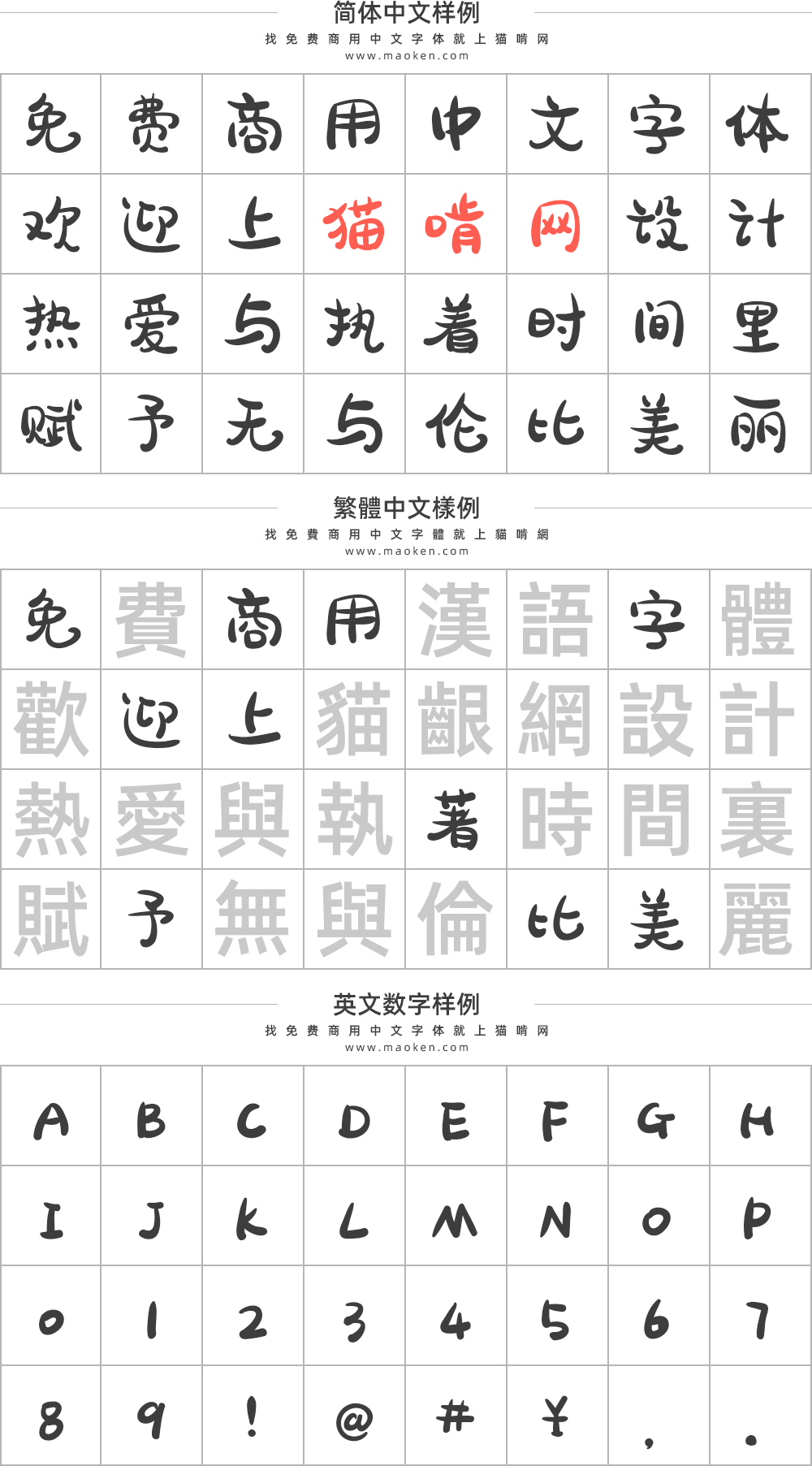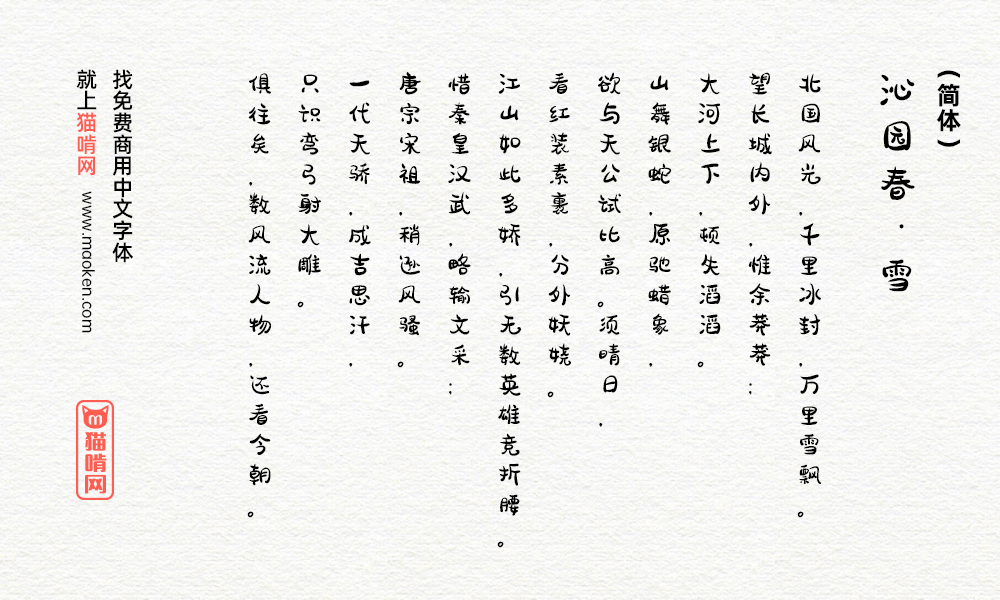
胡晓波骚包体:这个胡晓波是真的非常骚
字体作者:胡晓波 (中国大陆) 字体字重:1个
字体作者:胡晓波工作室(中国大陆)字体字重:1个
2019年12月23日,在圣诞节前夕,站酷人气设计师胡晓波在庞门正道公众号上一口气发布了三款可免费商用的中文字体。这三款字体分别是胡晓波真帅体胡晓波骚包体胡晓波男神体,我们来认真看看这三款字,命名非常骚气,完全符合胡晓波的性格。可以连起来看,一句话说完三个字体:一个骚包的真帅男神。
这三款字体,一共动用了胡晓波工作室7位同事,前后做了1年。人多力量大,就如庞门正道轻松体,80位同学参与,2个月就搞定,但是人少的话,就靠发工资了。这三款字体成本大概在人民币60万左右,所以说啊,所有的好东西,都是钱堆出来。
胡晓波骚包体字型设计十分趣萌可爱,整体字形圆润饱满,十分讨喜。特别适合母婴类,儿童类,或者是偏可爱风格的海报、标题等的设计。详细的设计案例请拉到本文未端查看。